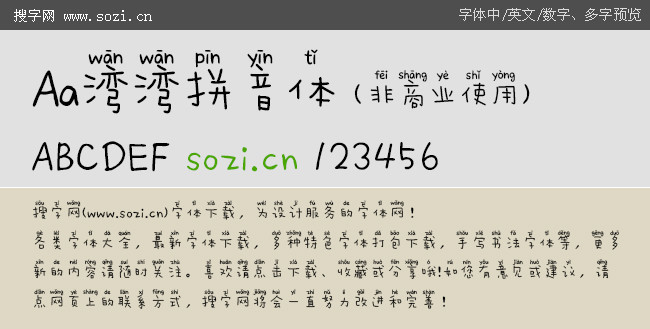
Aa灣灣拼音體
搜字網(wǎng)給大家提供一款A(yù)a灣灣拼音體(非商業(yè)使用)中文字體下載,該字體是一款手寫字體,字體筆觸纖細,并帶有拼音,具有很好的視覺感,適用于平面宣傳設(shè)計、網(wǎng)頁設(shè)計、海報設(shè)計等應(yīng)用(此字體為個人非商用版,商用可以聯(lián)系QQ:1006760504)。